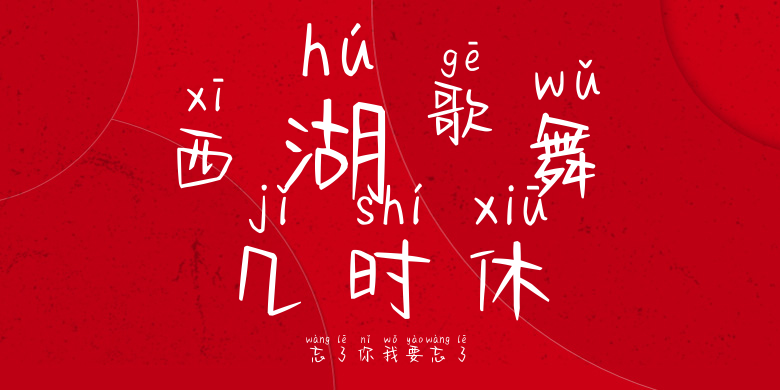
忘了你我要忘了
忘了你我要忘了,这款字体结构工整、笔画清晰,兼顾美观与易读性,适用于标题、正文、海报、包装、LOGO 等多种场景。字形优雅稳定,风格百搭耐看,适配日常排版与创意设计,让文字呈现更舒适、更具质感。忘了你我要忘了一笔一画,皆是细节,以均衡的比例、流畅的线条打造舒适视觉体验,字形端正大气,风格简约现代。无论是商业设计、品牌宣传还是日常排版,都能轻松驾驭,让文字更有格调与力量。忘了你我要忘了字体下载。